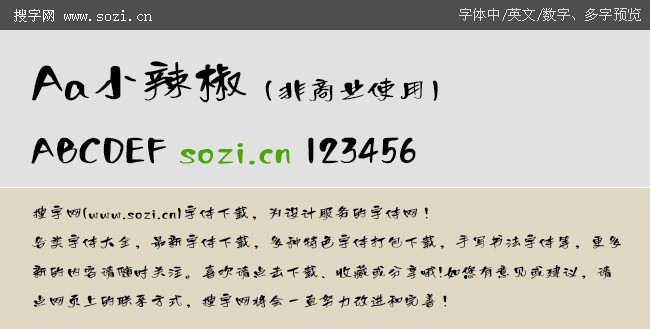
Aa小辣椒(非商業(yè)使用)
搜字網(wǎng)給大家提供一款A(yù)a小辣椒(非商業(yè)使用)中文字體下載,該字體線條粗壯有力,左邊粗壯,右邊纖細(xì),其視覺(jué)閱讀極具層次感,適合包裝畫(huà)冊(cè)等兒童卡通宣傳廣告等應(yīng)用(此字體為個(gè)人非商用版,商用可以聯(lián)系QQ:1006760504)。